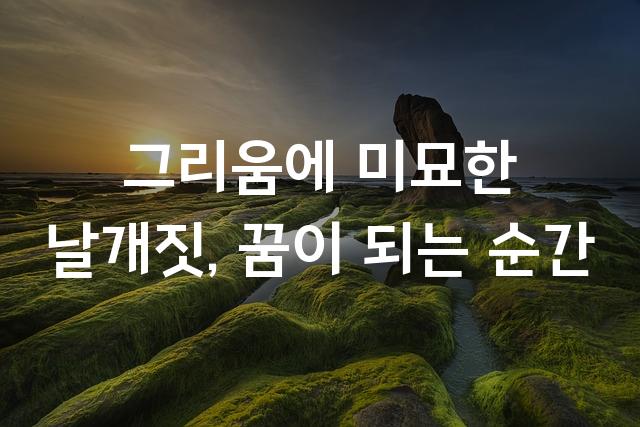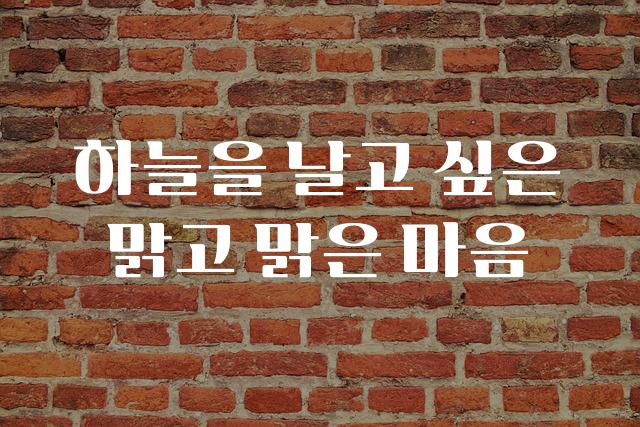
티웨이항공체는 티웨이와 폰트랩(주)가 협력하여 제작한 현대적인 굴린 고딕 폰트입니다. 독창적인 곡선과 깔끔한 라인이 특징으로, 독자의 감성을 자극하는 디자인이 돋보입니다.
티웨이항공체은(는)
기본 고딕 계열의 생김새를 가지고 있으며
웹/앱 디자인, 카페 메뉴, 소셜 미디어 등에서 자주 활용되며, 효과적인 메시지 전달에 적합합니다.
이 폰트는 광고/마케팅, 기술/IT, 관광/여행 분야에 잘 어울리며,
명확한, 편안한, 전문적인 느낌을 담고 있는 것이 특징입니다.